Justine Sutton a réalisé cette typographie avec de petits bouts de papier. CCe projet me fait penser un peu au style des créations de Yulia Brodskaya. Du chouette boulot 🙂
Typographie en papier
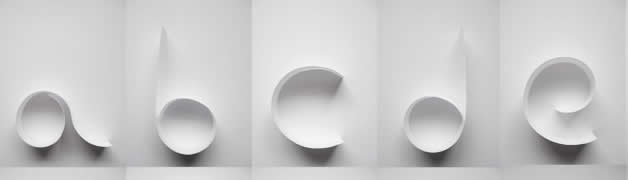
Justine Sutton a réalisé cette typographie avec de petits bouts de papier. CCe projet me fait penser un peu au style des créations de Yulia Brodskaya. Du chouette boulot 🙂